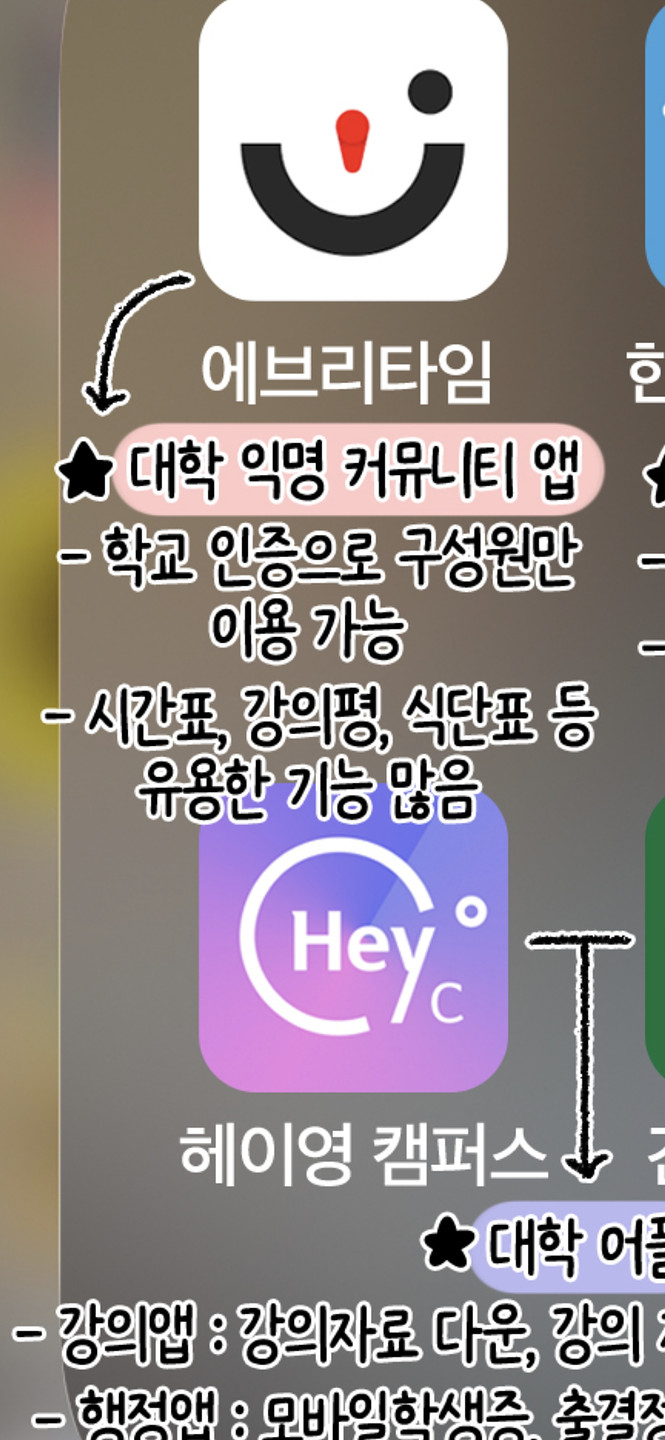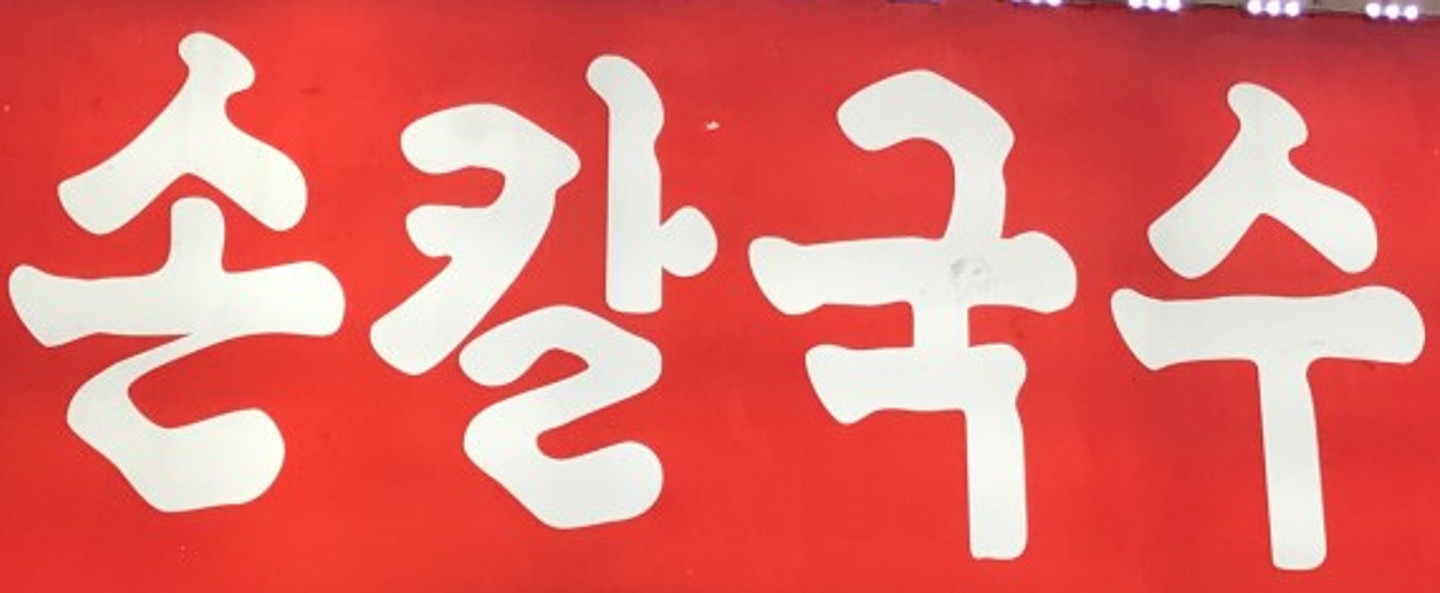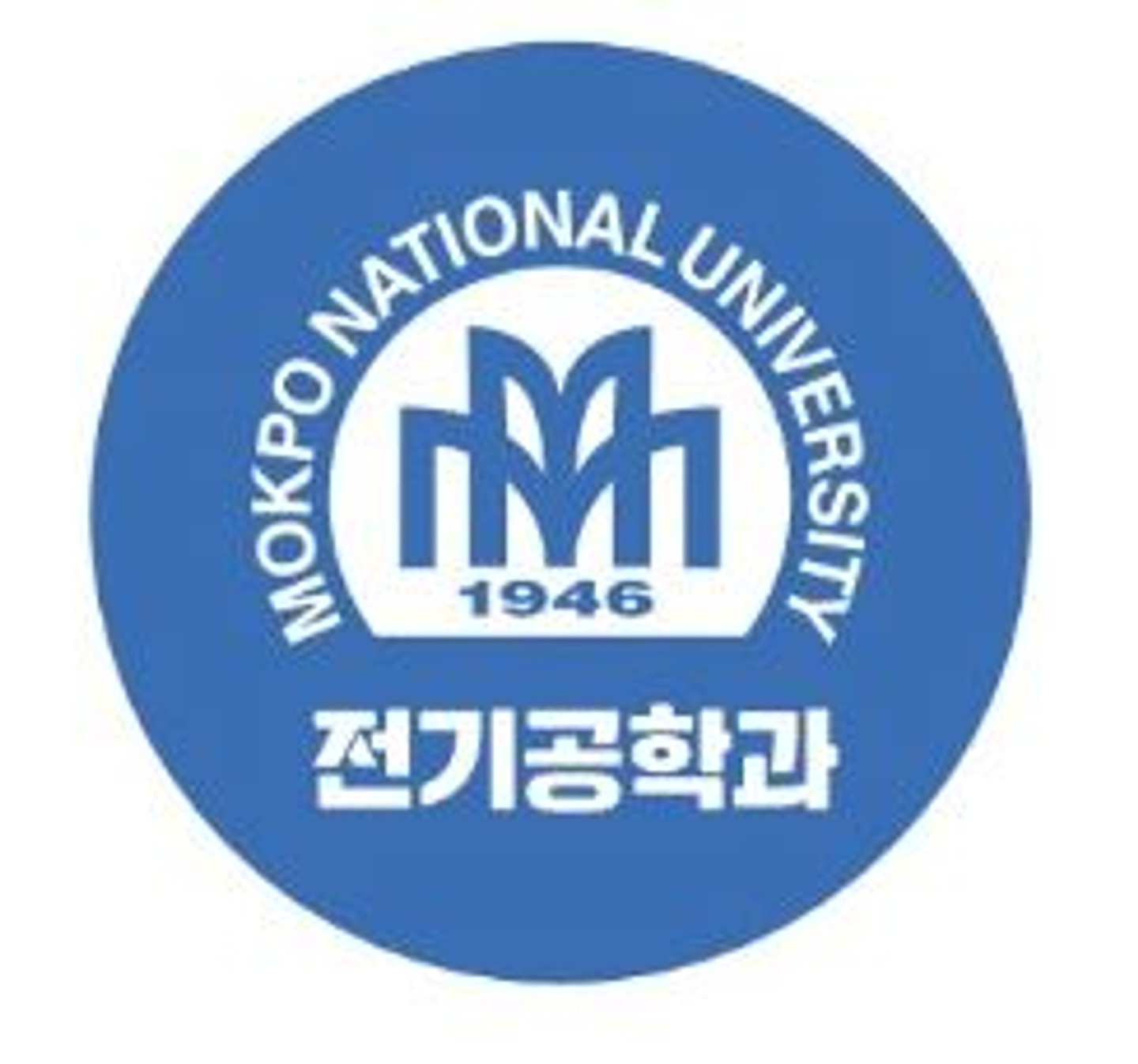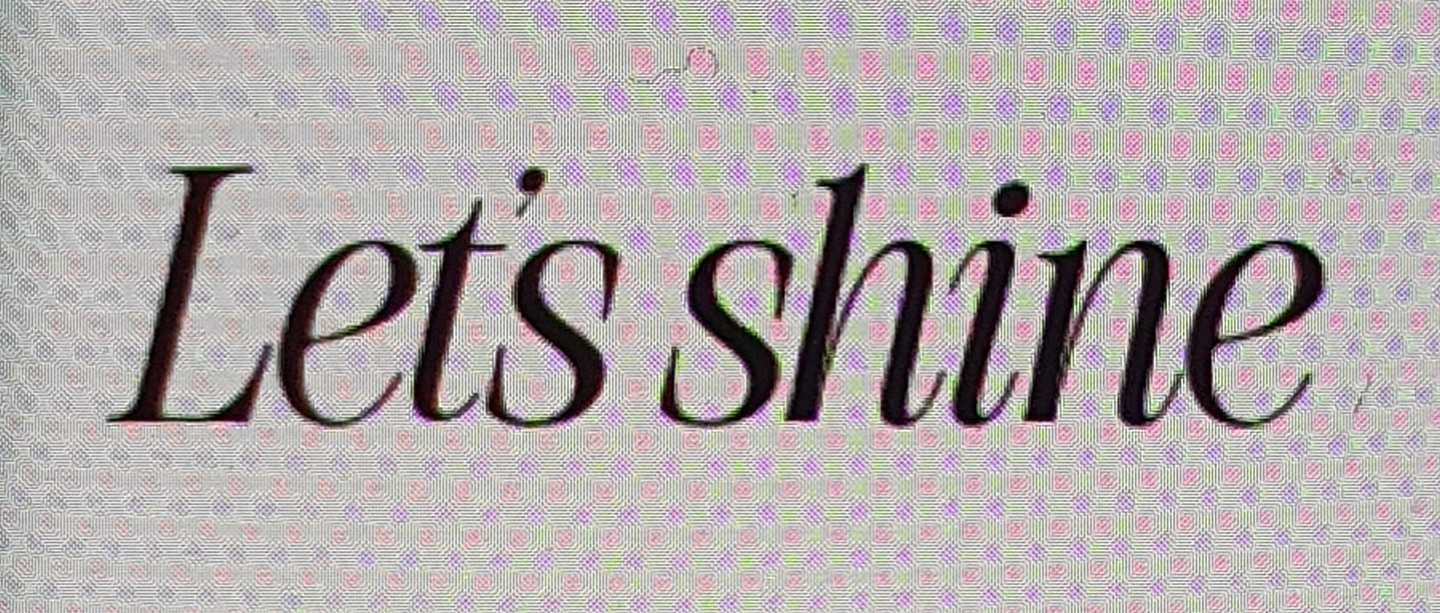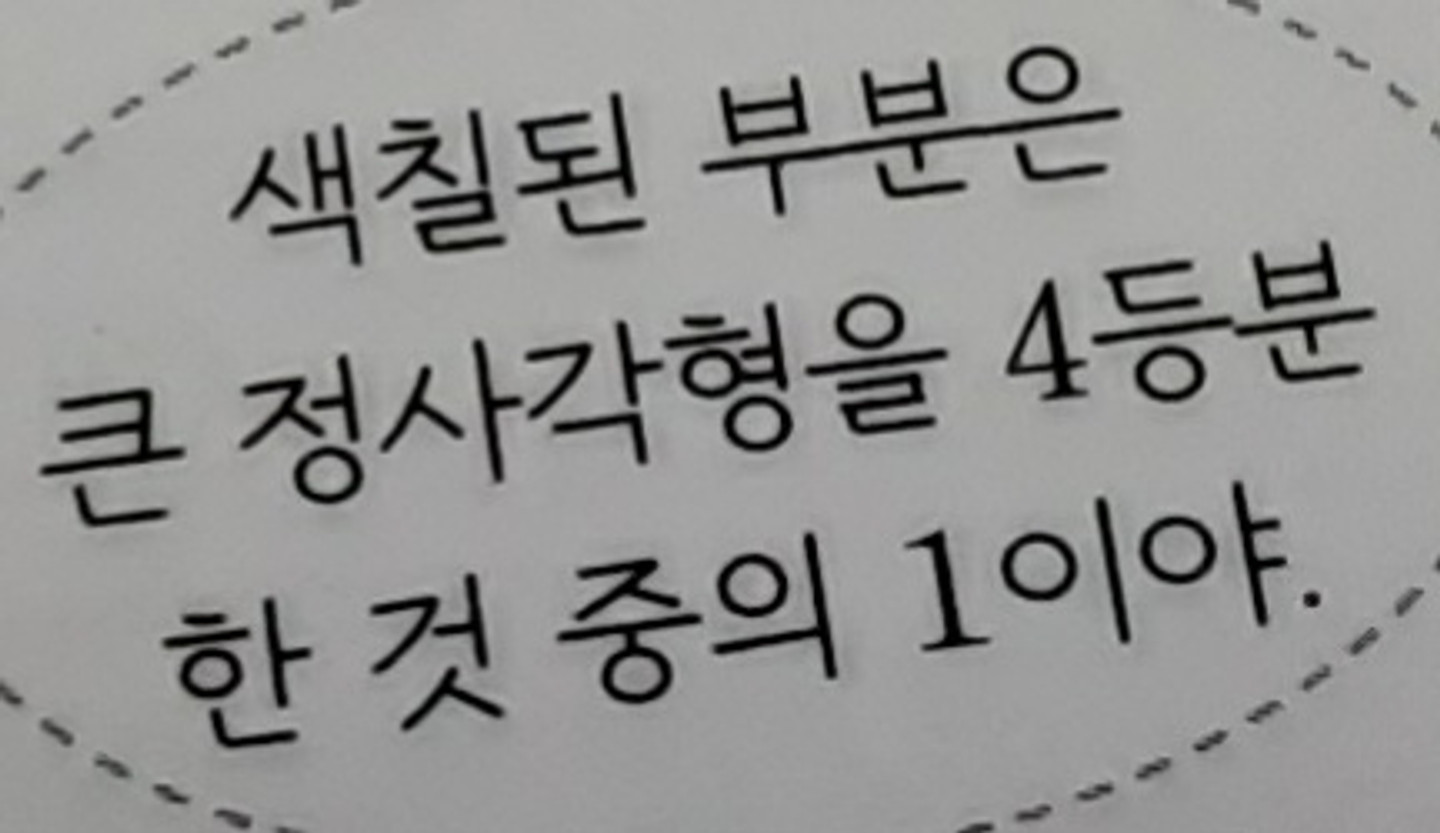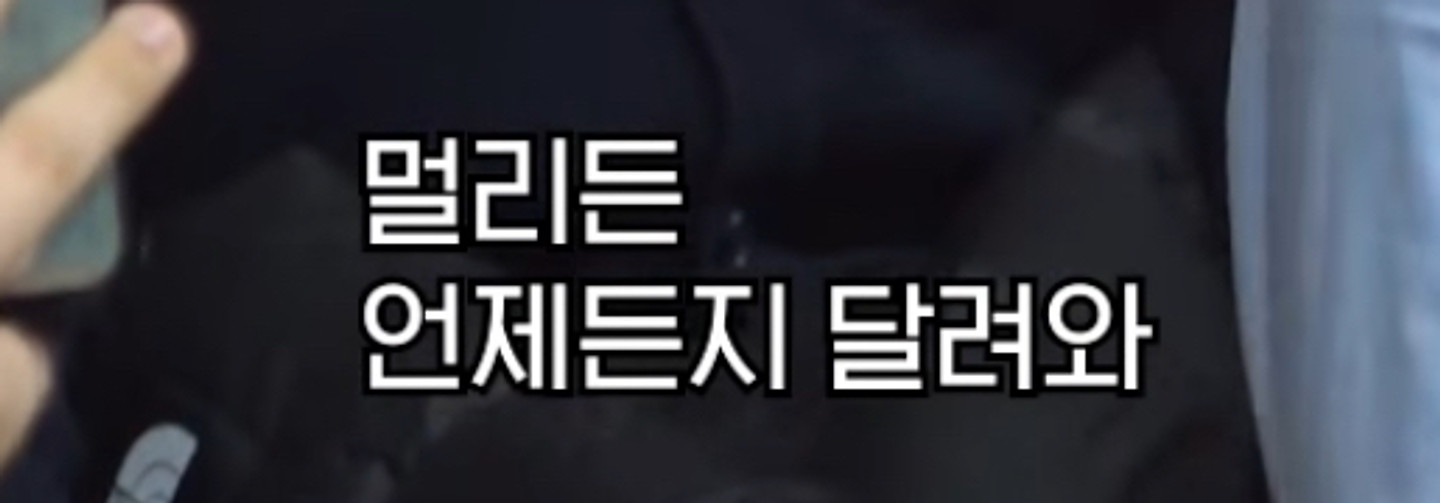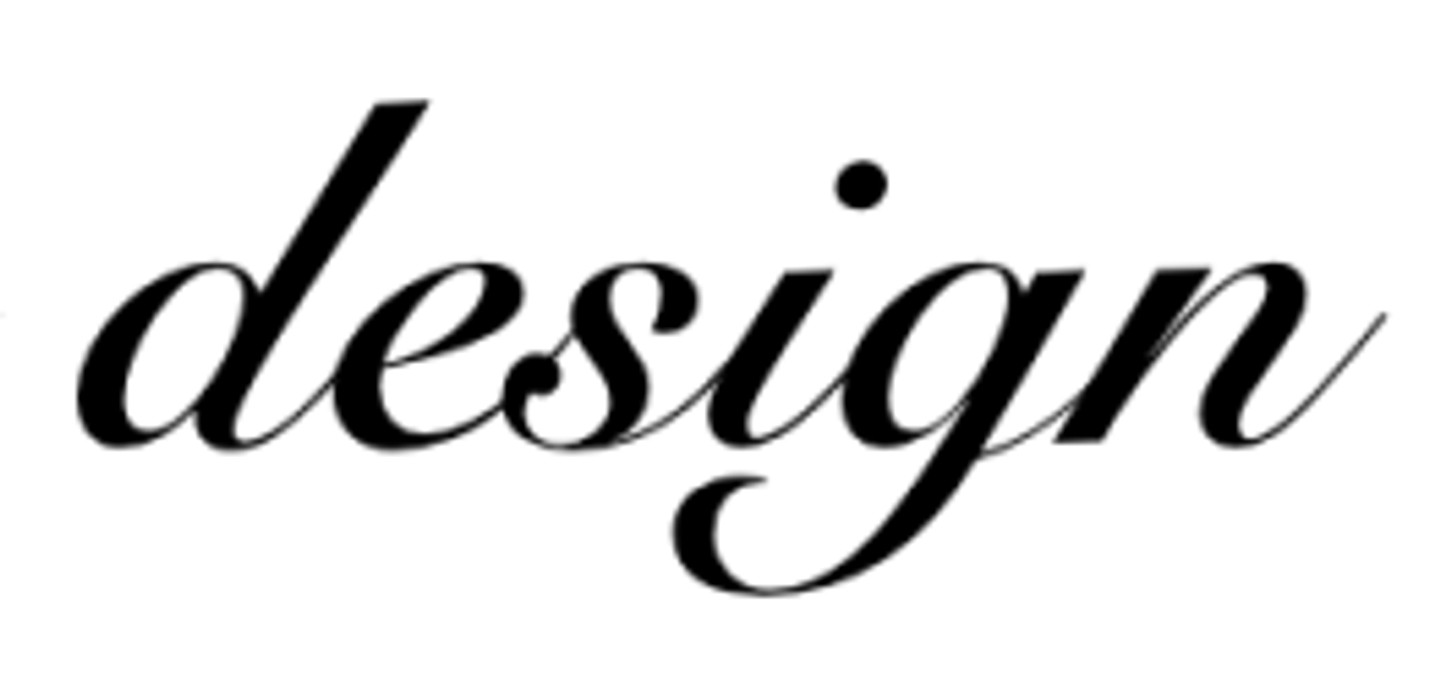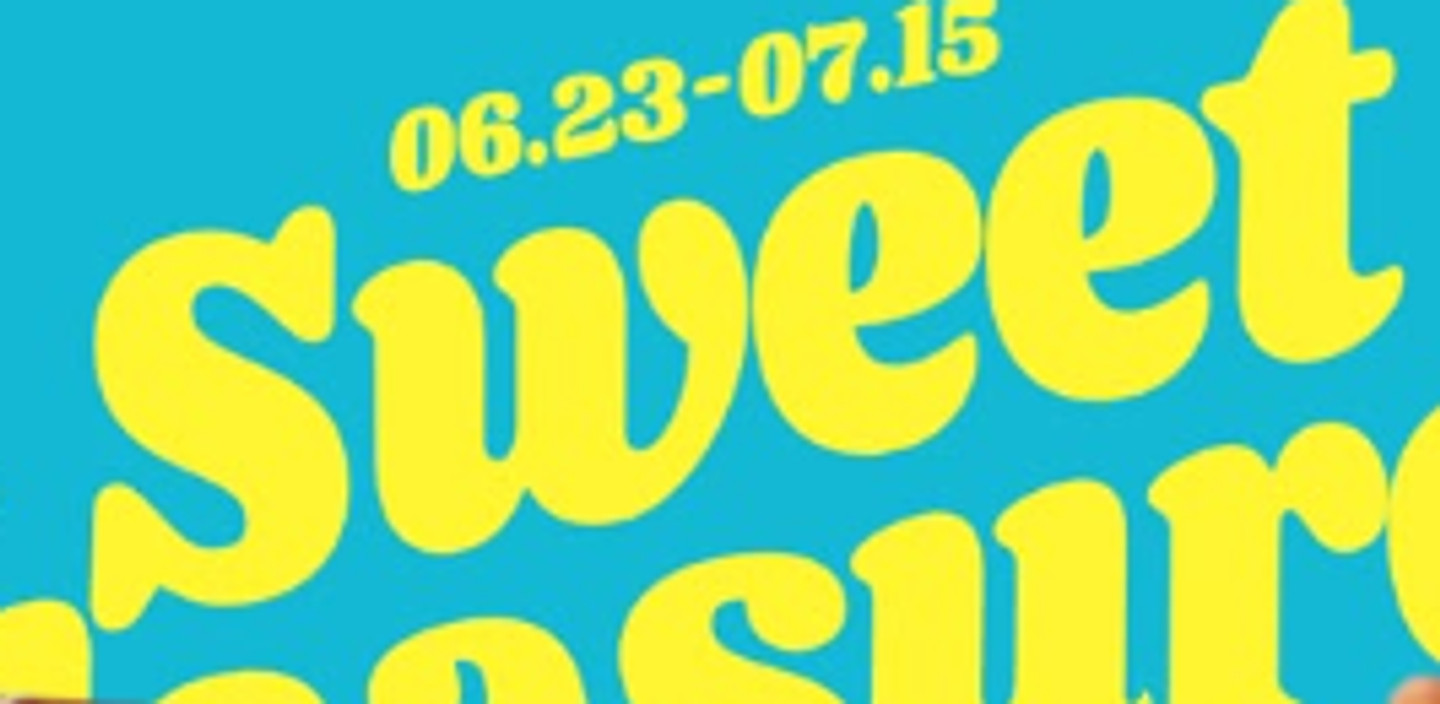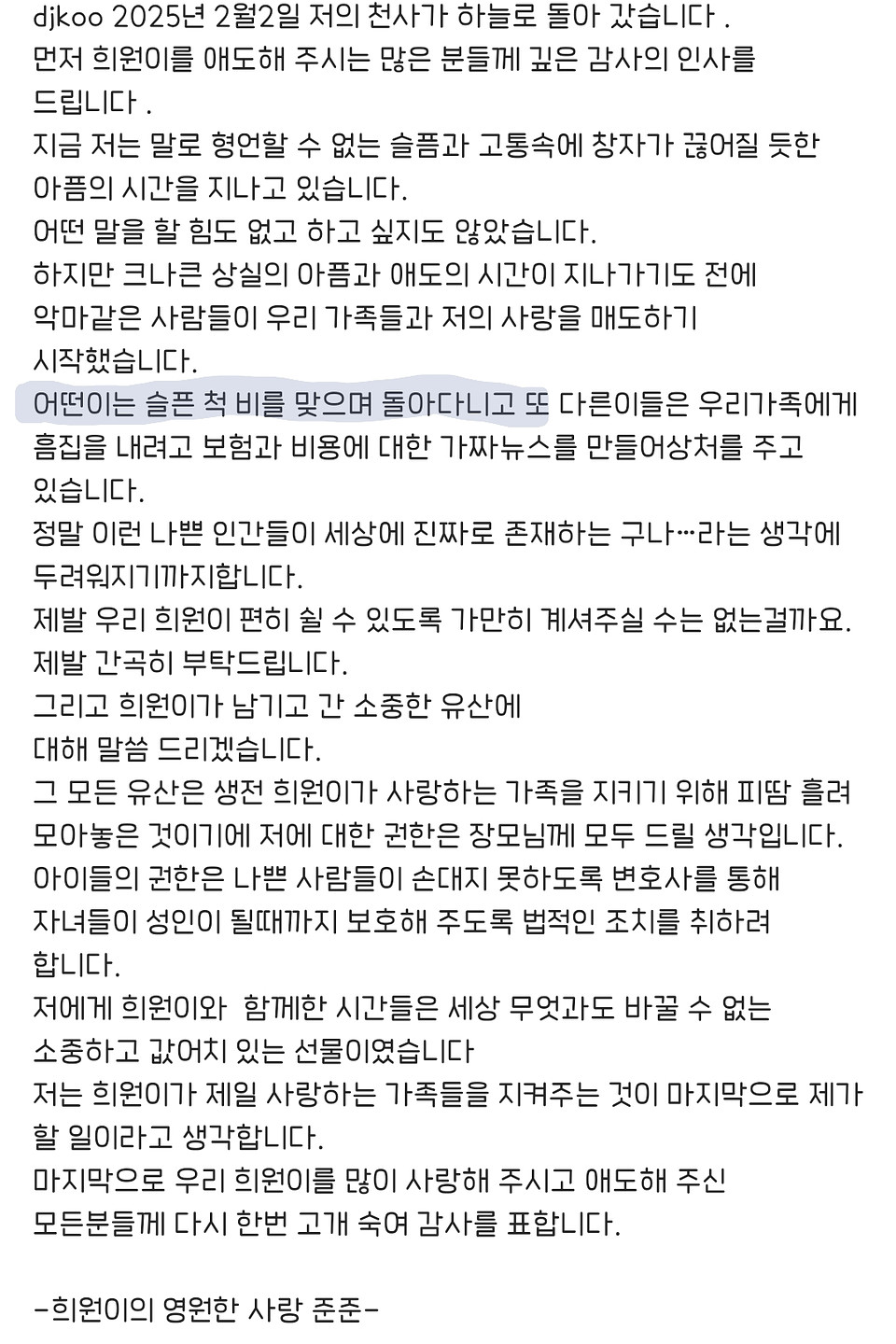
지인분이 구매하기 전 확인했는데 글씨체가 손글씨치고 너무 균일하고 종이가 말린것에 비해 글씨가 말리지 않은것을 발견하셔서요, 혹시 무슨 글씨체인지 아시는분 계실까요...?
글씨 무슨체일까요?
무슨 폰트인지 알려주세요..!
하단자막 폰트명 뭘까요
해당 자막에 쓰인 폰트 어떤거일까요ㅠㅠ
동그라미친 폰트 이름을 알고 싶습니다
문구의 폰트가 어떤것인지 아실까요ㅜㅜ 아무리 찾아도 모르겠어서요ㅜㅜ
이 폰트 궁금합니다ㅜㅜ 어떤 폰트일까요
이 폰트 무슨 폰트 일까요..ㅠㅠ
리코 채팅창 폰트 뭔가요 ?
여럿 챙기느라 고생하십니다 < 자막 폰트 궁금합니다!
이 폰트 이름 뭔가요?
이 폰트에 대해서 알려주세요 부탁드립니다!
이것도 좀 부탁드립니다!
이 폰트좀 부탁드립니다!
혹시 이 폰트 아실분 계신가요 윤고딕 200번대, 헤움네모고딕 비슷하긴 한데 미세하게 다 다르네요 ㅠㅠ
이 폰트 어떤걸까요?
무슨 폰트인지 알수 있을까요??
이 폰트 무엇인지 아시는분 계실까요 ㅠㅠㅠ
이 폰트는 무슨 폰트일까요?
이 폰트 뭔가요??
“영화같다”에 사용된 폰트 알 수 있을까요?
무슨 폰트인가요?????알려주세염
물리치료실 폰트 어떤건지 알 수 있을까요? 미리 감사합니다!
무슨폰트일ㄲㅏ요? 직지 일상로그 무슨로그랑 비슷하긴한데 같은건 아닌거같아서요 ㅠ
요 폰트는 무엇일까욥?
라이브 글씨체 아시는분 계실까요?
세련민간요법연구 글씨 문의 드립니다.
어떤 폰트일까요?...
폰트뭔가요?
손글씨 폰트
이 폰트 아시는분 ㅜㅜ 부탁드립니다. 회기동이랑 안녕마을 폰트 두개가 다른 것 같은데 무슨폰트인지 모르겠어요 고도랑 고양덕양도 비슷한데 대조해보니까 아니더라구요 ㅠㅠ
이폰트 뭔지알수있을까요??
자막에 사용된 폰트가 궁금합니다
이 폰트 무슨 폰트인가요ㅠㅠ
every piece 부분 폰트가 궁금해요
어떤 폰트 인가요?
폰트박사님덜...
이게 무슨 폰트인지 너무 궁금해요!!!
이 폰트 무엇인지 알고싶습니당 ㅠ
혹시 이 폰트 무엇 일까요 ㅠ? 제발 알려주세용 ㅠ
이 폰트 이름 알고 싶습니당 ㅠ
혹시 이 폰트는 이름이 뭘까용 ㅠ?
혹시 이 폰트 뭘까용ㅠ?
이 폰트 이름이 뭔지 궁금합니다
이 폰트명이 뭘까요?
무슨 폰트인지 알려주세요
이폰트 뭔지 아시는분 알려주십쇼 ㅠㅠ
신인감독 김연경 프로그램에 나오는 자막은 무슨 폰트일까요?
이 폰트 뭔지 아시는 분 계신가요!!! 크레파스 느낌이 너무 이쁘네요 ㅎㅎ
대한민국 야구 국가대표 등번호인데 무슨 폰트인가요?
드라마 ’달까지 가자‘ 방송중 자막으로 나오는 글씨체인데 아시는 분 있나요?ㅠㅜㅜㅜ